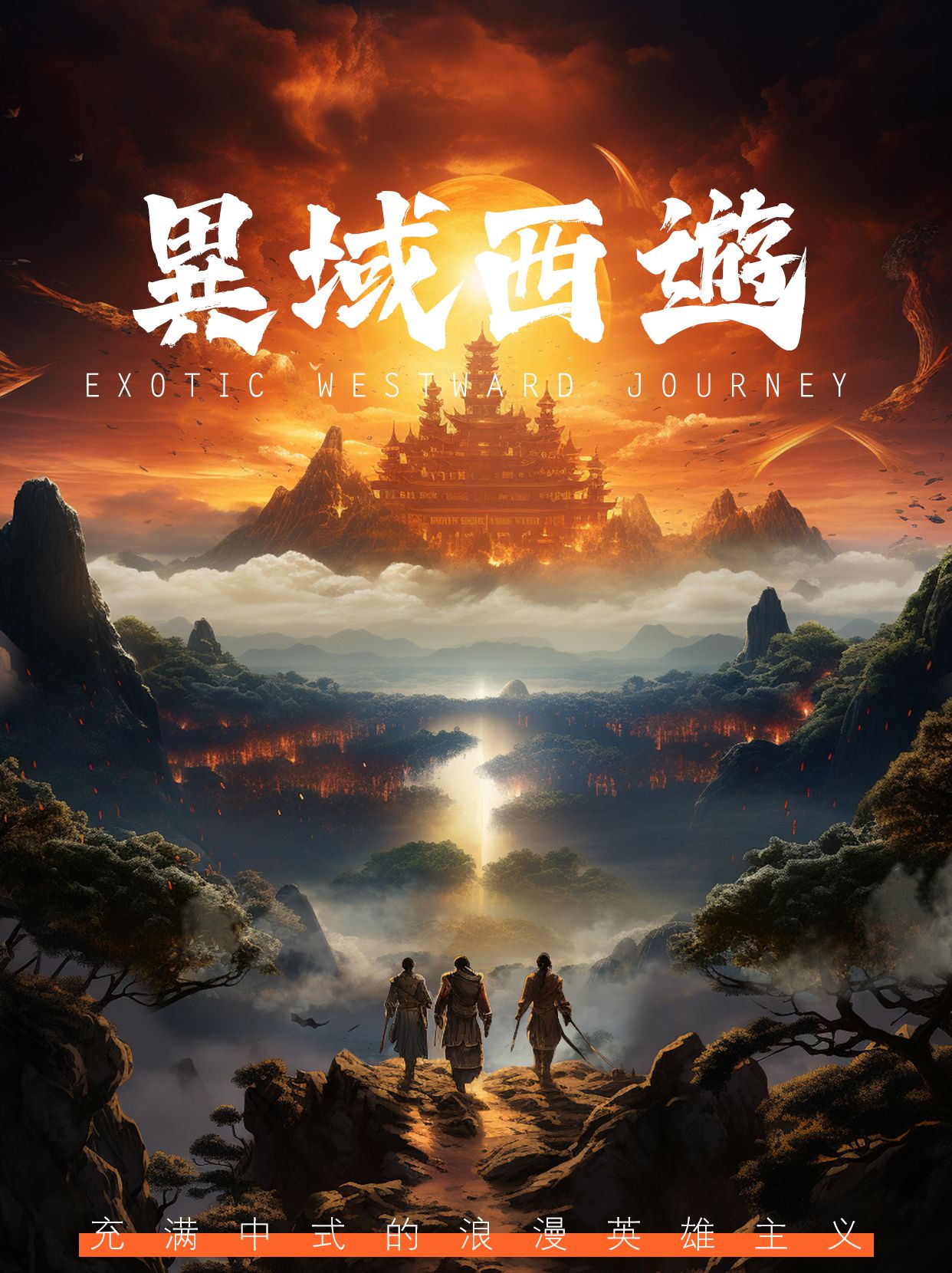
新国风书法字库|造字侠字库,仙魔神话类国风游戏字库
书法字体,就是书法风格的分类。以前的书法字体,传统讲共有行书字体、草书字体、隶书字体、篆书字体和楷书字体五种,也就是五个大类。在每一大类中又细分若干小的门类,如篆书又分大篆、小篆,楷书又有魏碑、唐楷之分,草书又有章草、今草、狂草之分。
而印近些年国潮兴起,是新国风字体的创新字体类型,在基础的书法字体的基础上进行创意的设计,以书法为字体骨架,在笔画以及风格上进行大胆创新的新国风字库。
造字侠字库便是新国风类的书法字库,多用于仙侠神魔游戏类海报宣传、LOGO设计等场景,代表字体:造字侠灵霄简繁 传神、造字侠伏魔简繁 传神、造字侠仗剑简繁 传神
造字侠灵霄简繁传神 是一款硬笔手写字,名字来源于《西游记》玉皇大帝的居所灵霄宝殿。字体笔画硬挺利落,字形古风劲萧,饱满均匀,结构布局沉稳,笔力劲健,适用于仙侠、网游等海报标题用字。
造字侠伏魔简繁 传神,笔墨浓厚,粗细对比较为明显,字体结构较为中正,字体里笔画的“勾、提、挑、捺”等笔画特点明显、夸张,极具视觉冲击力,单字结构收放自如。
造字侠仗剑简繁 传神,一款字形稳重、笔画张扬的书法字体。折、提、钩等部首干净利落、高度折叠,颇有豪侠仗剑江湖的潇洒之感。